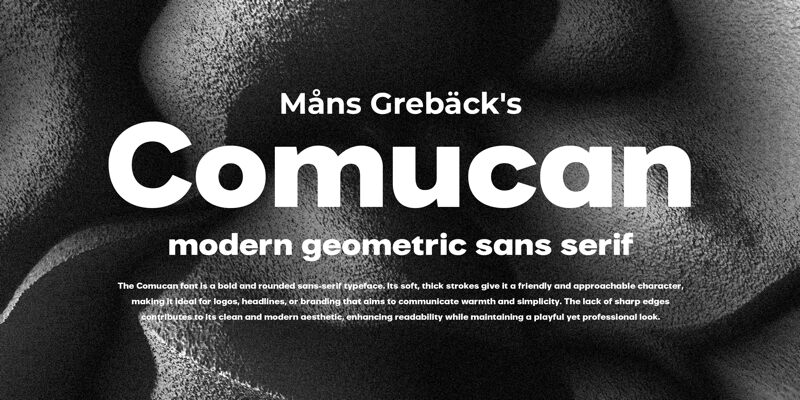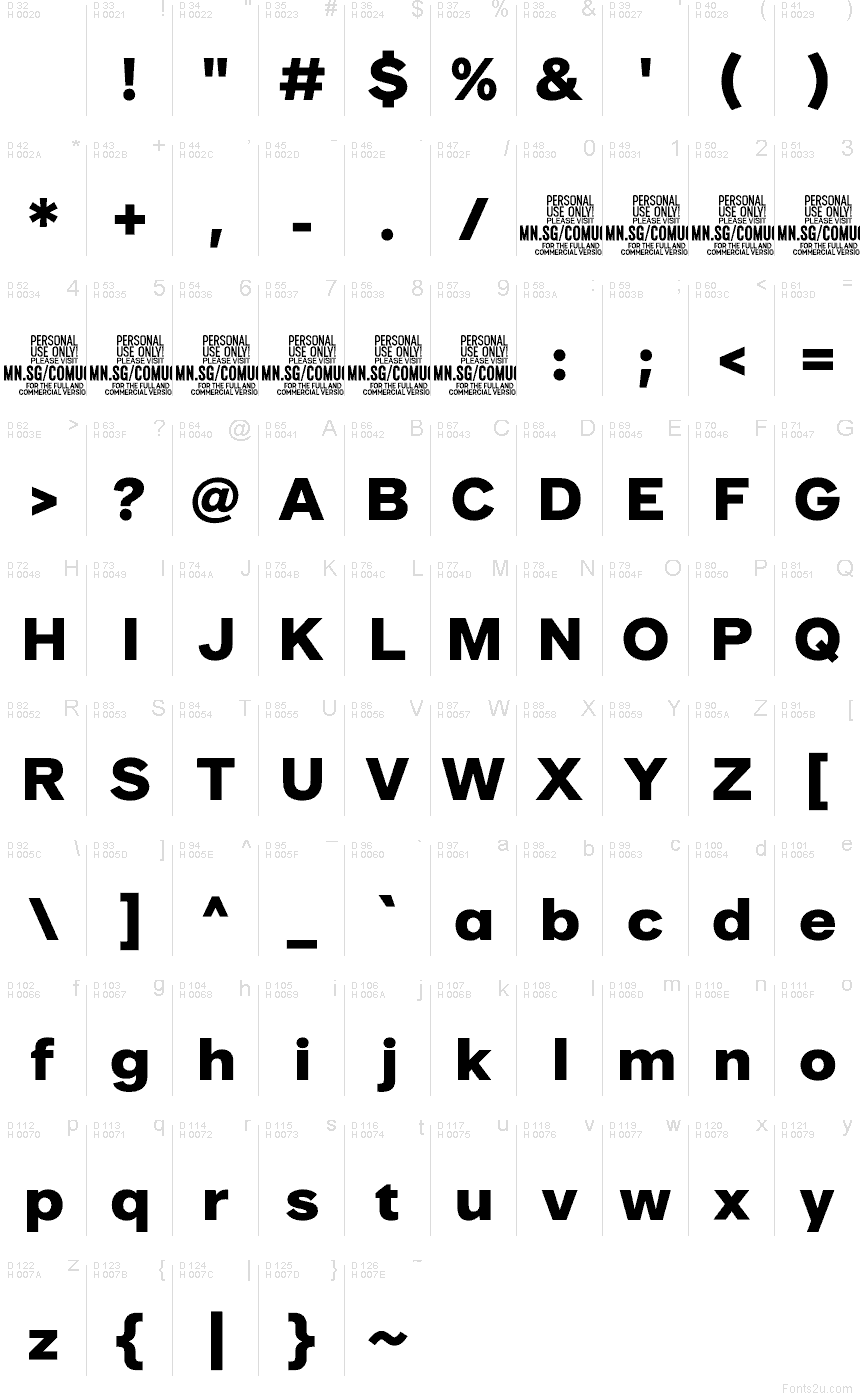
Comucan von Mans Greback ist eine kostenlose serifenlose Schrift, die sich durch breite, dunkle Formen und einen kompakten Rhythmus auszeichnet – dicht gesetzt, ohne dabei eingeengt zu wirken. Die abgerundeten Bögen und stumpfen Außenkanten verleihen ihr eine robuste, plakative Präsenz, während die wiederkehrenden geschwungenen Verbindungen verhindern, dass das Design zu hart oder mechanisch wirkt.
Diese Kombination ist ideal für Plakate, Verpackungen, Logo-Entwürfe, Album-Artworks und kurze Überschriften, bei denen eine prägnante Silhouette gefragt ist. Comucan eignet sich zudem hervorragend für App-Header oder Social-Media-Grafiken – besonders dann, wenn Sie eine schlichte Sans-Basis suchen, die dennoch kraftvoll und grafisch wirkt.